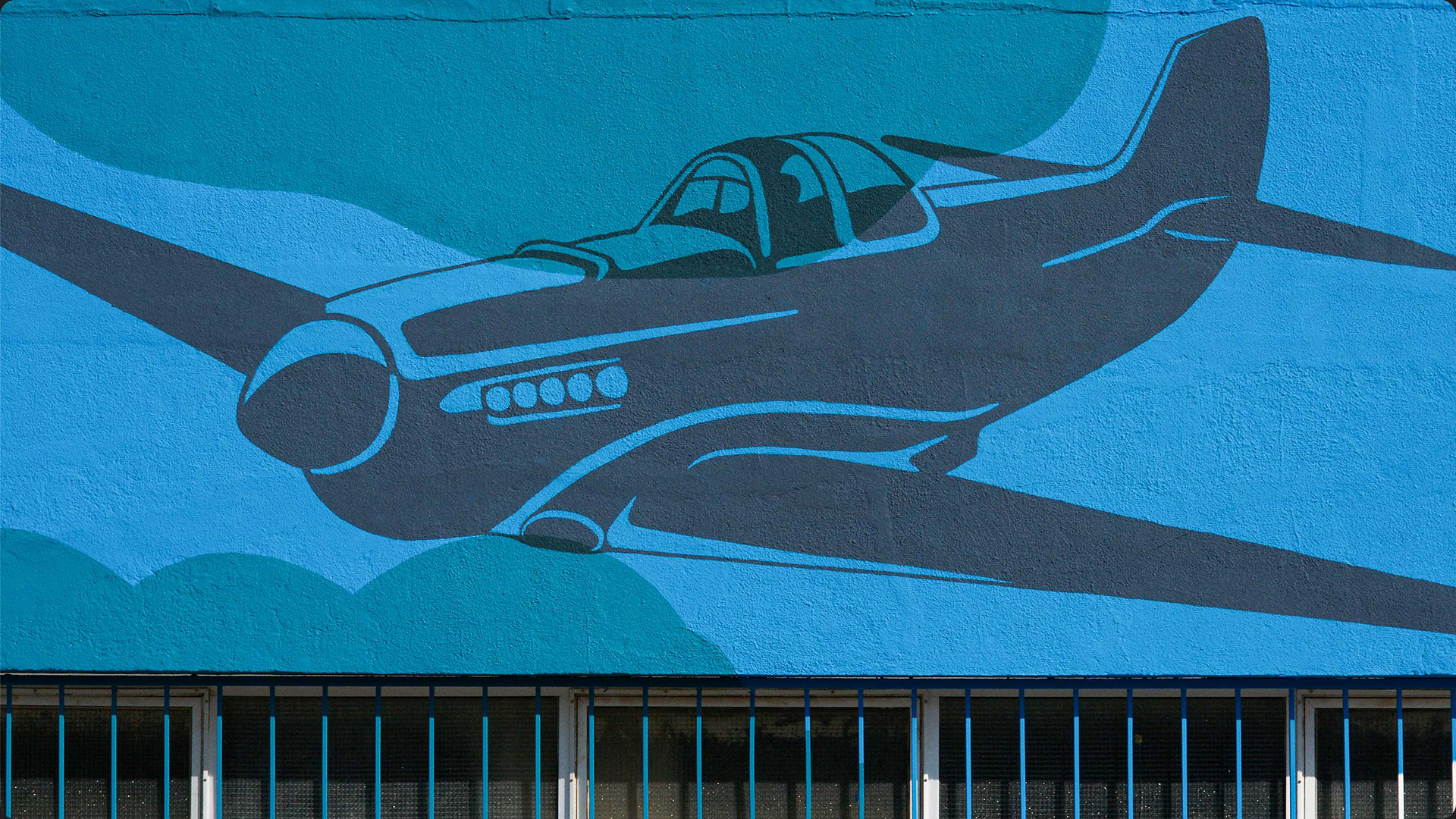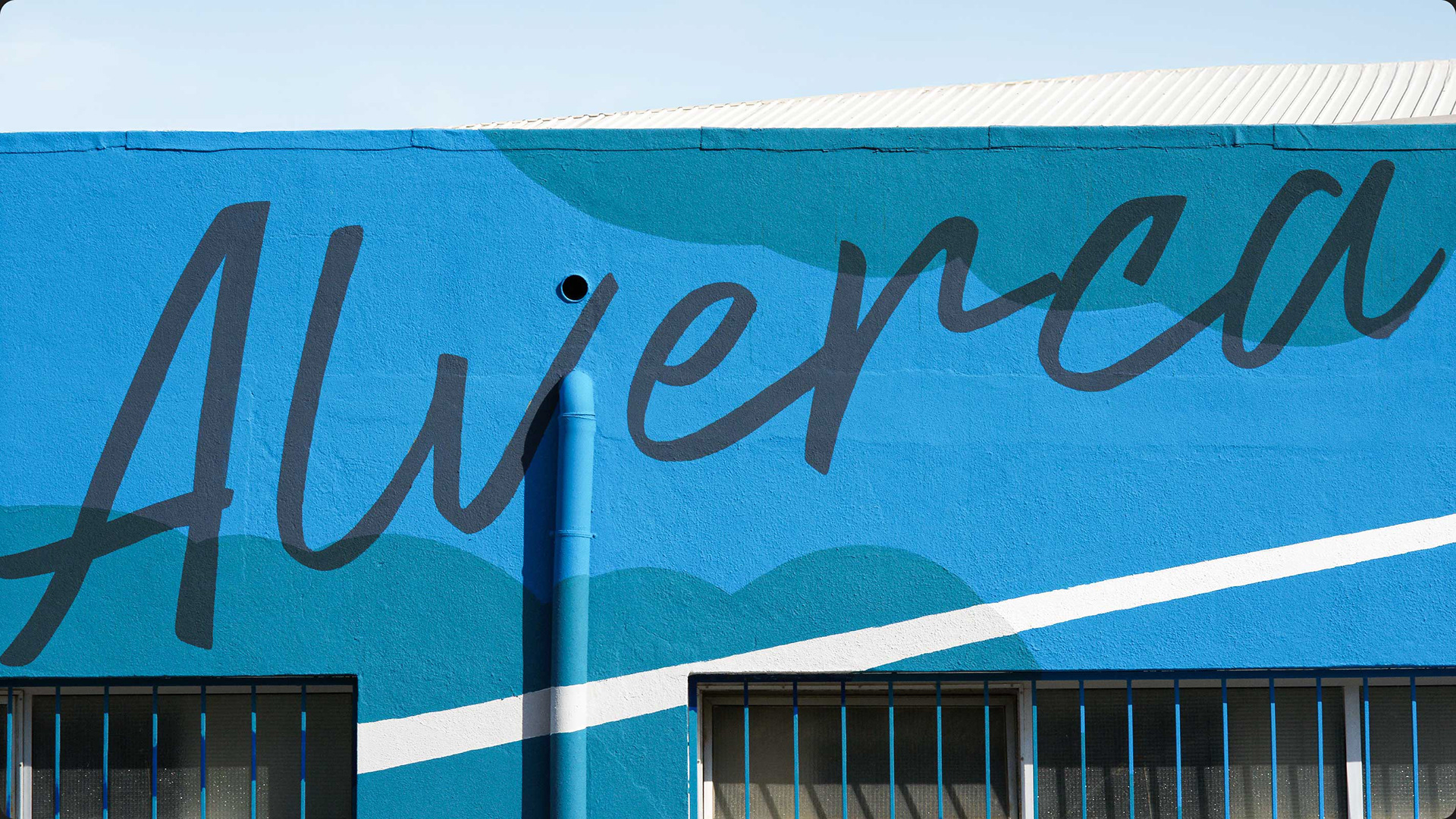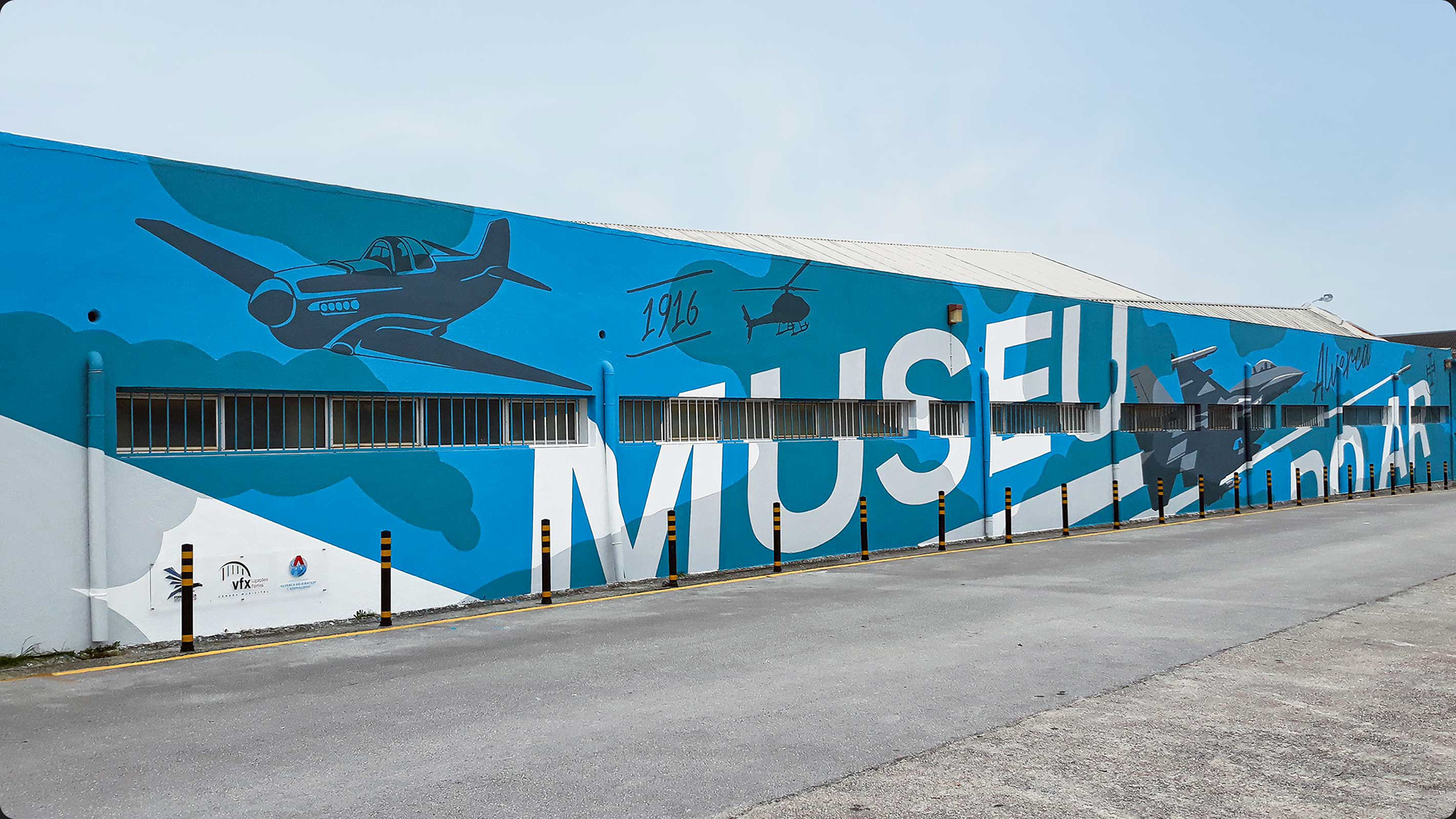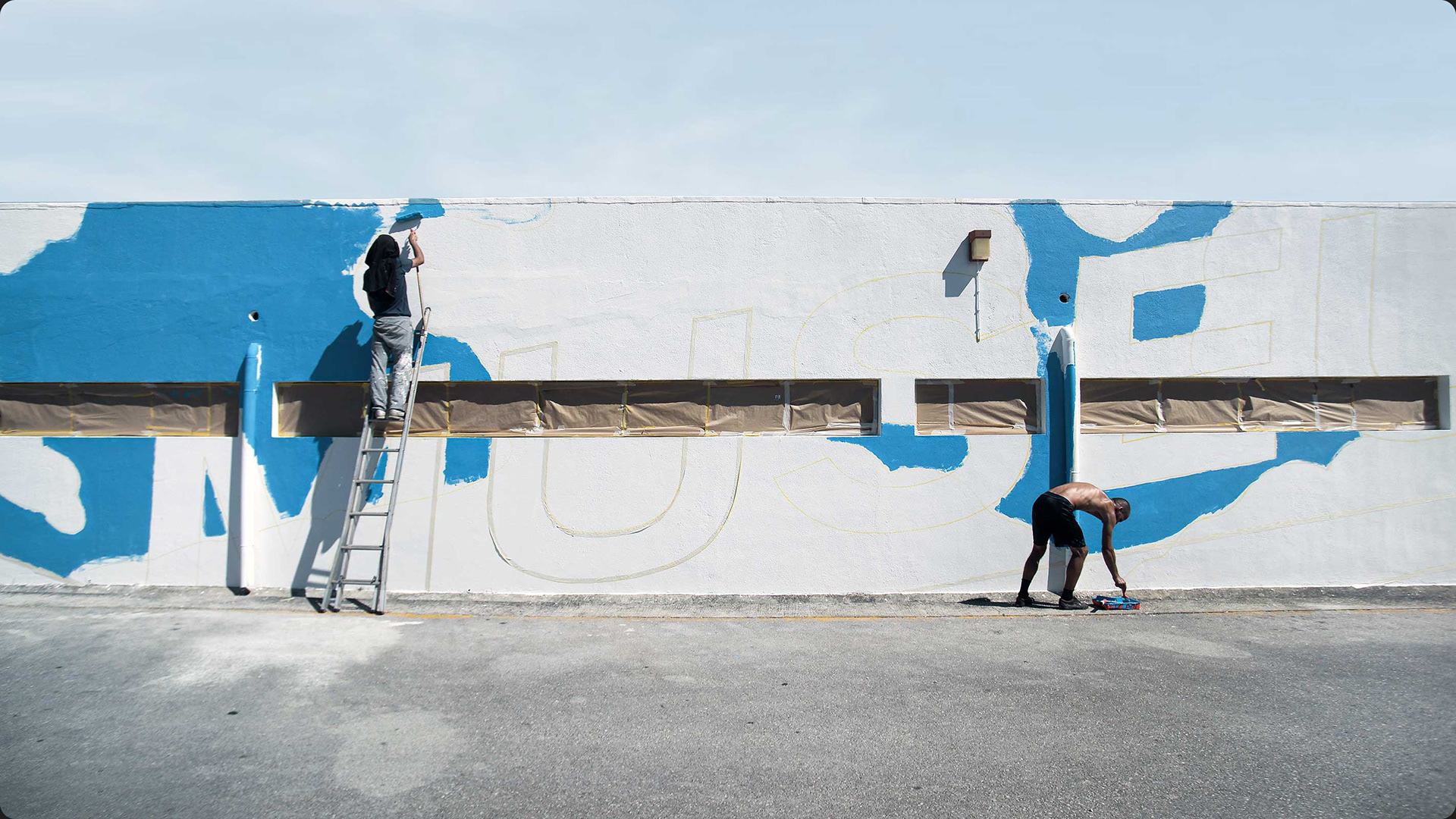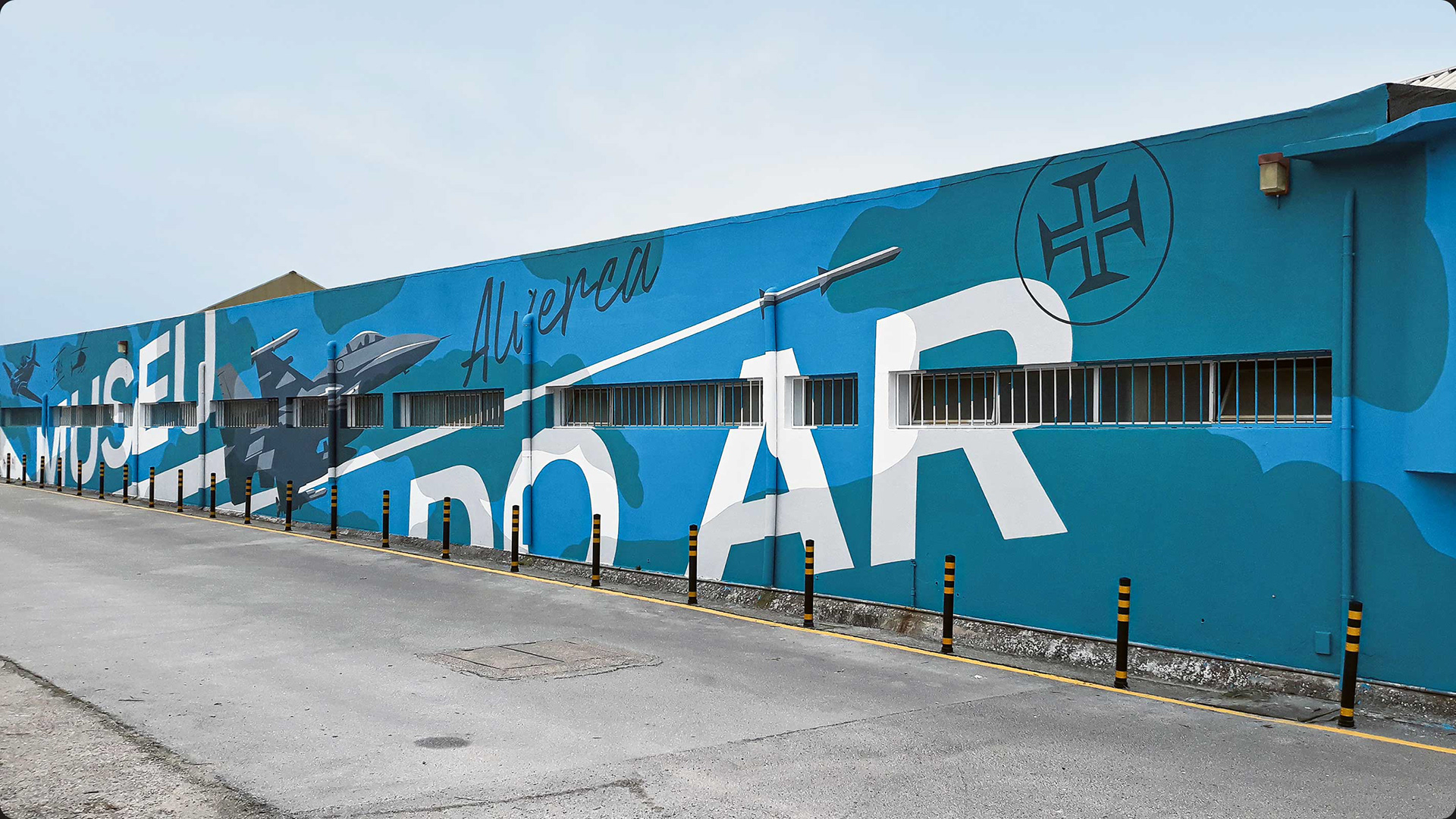
Alverca do Ribatejo está ligada à história da aviação. A convite da Força Aérea Portuguesa, inscrevemos parte dessa história no Museu do Ar. O mural, posicionado junto à linha de comboio, inspirou-se na velocidade e perícia dos aviadores, tornando o espaço acolhedor, acessível à comunidade e visível para as milhares de pessoas que diariamente por ali passam.